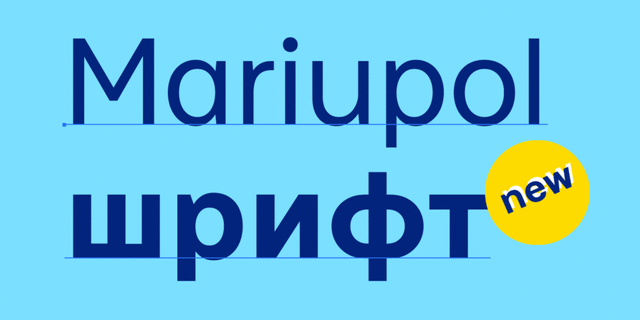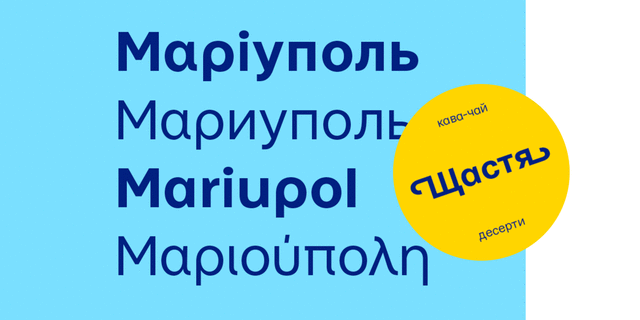
Шрифт Mariupol — это геометрический гротеск, вдохновленный, с одной стороны, швейцарской и немецкой плакатной графикой, с другой — современными технологическими гарнитурами San Francisco, Graphik, Walsheim. Доступен в трех базовых начертаниях: обычном (Regular), полужирном (Medium) и жирных (Bold). Также в комплект добавлено специальное начертание с пиктограммами (Symbols). Поддерживаются украинский, английский, греческий, русский языки. Сейчас шрифт официально представлен в городской навигации Мариуполя, его можно увидеть и на трамваях, и на бордах с поздравлениями мэра. Более того, каждый желающий может скачать этот шрифт и самостоятельно что-то написать по-мариупольски. Шрифт Mariupol разработали Андрей Шевченко и Сергей Родионов в 2017 году.
Ассоциации c семейством MariupolКачества и характер:
деловой, строгий, чистый, элементарный, минималистичный, самостоятельный, ответственный, западный, точный, ровный, убедительный, прямоугольный, стабильный, статичный, простой, нейтральный, современный, глобализированный, глобалистичный, монотонный, логичный, прагматичный, практичный, твердый, лаконичный, доступный, серьезный, железный, стальной, надежный, уверенный, устойчивый, машинный, инженерный, индустриальный, техногенный, городской, четкий, чертежный, урбанистичный, обязательный, урбанистический, оригинальный, понятный, интересный, гладкий, дружелюбный, комфортный, удобный, важный, архитектурный, рабочий, сильный, мотивирующий, армейский, мужественный, резкий, острый
инструмент, химия, математика, урбанистика, промышленность, техника, код, чертеж, конструктор, инженер, автоматика, ГОСТ, город, навигация, наука, дизайн, электроника, программирование, архитектура, море, аптека, лекарство, медицина, рентген, банкнота, монета, отдых, туризм, станок, тара, электростанция, энергетика, армия, оружие, машиностроение, завод, мотор, пресс, каска, униформа, вагон, авиация, самолет, страйкбол, стройка, строительство, топливо, порт, транспорт, архитектор, рабочий, логистика, робот, сталевар, интернет, общество Стилистика: